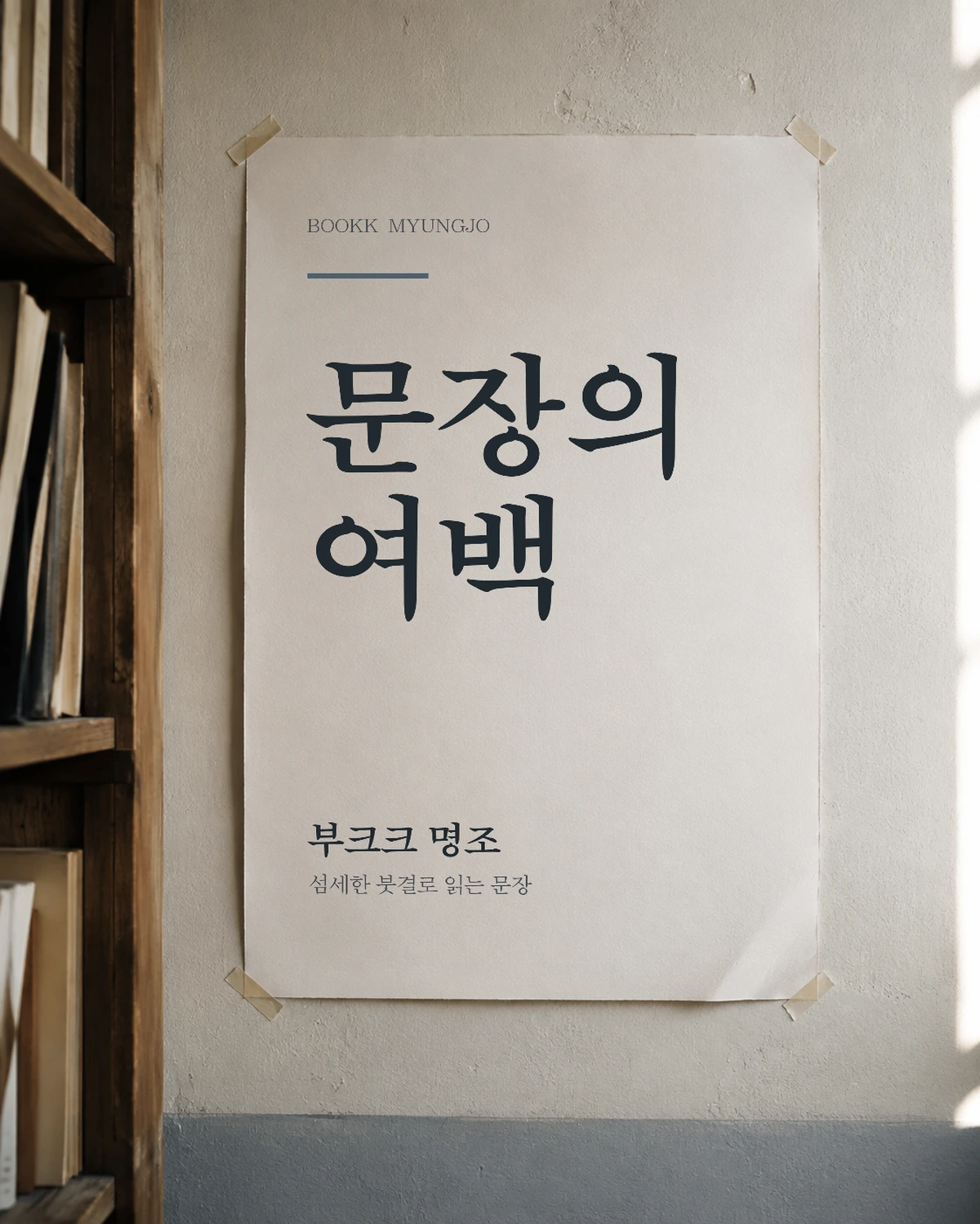
부크크명조 무료폰트
부크크명조 — 부크크에서 배포하는 무료 폰트입니다. 붓으로 쓴 듯한 섬세한 획과 안정적인 구조가 어우러진 현대적인 바탕체
자가출판 플랫폼 부크크가 배포하는 서체 두 벌 가운데 부리 쪽입니다. 책을 쓰는 작가와 읽는 독자 모두를 위해 만든 본문용 서체로, 종이책 인쇄에 맞춰 설계됐다고 소개됩니다.
부크크가 직접 쓴 조형 설명은 공개돼 있지 않습니다. 파일에서 재어 보면 받침 유무에 따른 높이 차가 거의 없는 네모틀이고, 자면을 채우는 비율이 낮아 인상이 가볍고 여백이 넉넉합니다. 긴 글을 얹었을 때 눈이 덜 피로한 쪽에 가깝습니다.